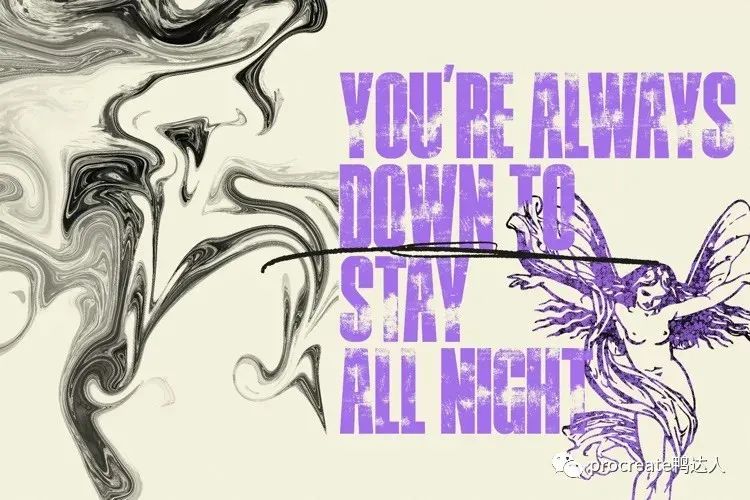
赛博朋克风手写字体来了,极具设计感,有预感会火!【794期】
01赛博朋克侵略风手写字体
Strila是一款赛博朋克夸张倾斜侵略感的英文手写字体。倾斜的字形、动感的笔画,搭配浓艳的色彩背景,非常的赛博朋克。夸张的风格可以完美的和音乐、体育、艺术等主题相融合。素材包含大小写字符、数字、标点符号和多语言支持,提供otf格式
02
动感机械风英文装饰字体
Adlm是一款动感机械风倾斜线条组成的英文装饰字体。奇特的字形、略微倾斜的笔画、笔直的线条结构设计,看起来极具视觉冲击力。适合任何需要科技感奇特主题风格的项目设计应用。您可以将它用于音乐、体育、艺术等项目的设计中。素材包含大写字符、数字和标点符号,提供otf格式。
03
朋克风粗糙字体分享
SO FAR SO GOOD是一款朋克风粗糙大胆墙体喷绘的英文无衬线字体。现代的无衬线字形,结合粗体拉长的字形设计,和粗糙的纹理效果,看起来就像墙体喷绘一样真实自然。非常适合用于大标题、海报、标签、邀请函、婚礼、招牌等项目的设计应用。素材包含大写字符、数字和标点符号,提供otf和ttf格式。